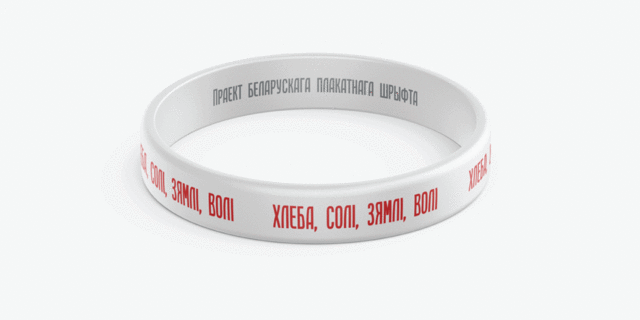
Гарнитура Хлеба Солі Зямлі Волі – это графическое исследование, объединяющее традиционный грубый жирный плакатный шрифт с гуманистическими нотками эпохи Возрождения. Гарнитура унаследовала некоторые идеи Франциска Скорины, чтобы добавить гуманистический оттенок. Название навеяно стихотворением Янки Купалы. Это современный белорусский титульный плакатный шрифт, но его можно легко использовать в любых случаях, когда необходимо сочетать строгие линии традиционных плакатов с гуманистическим стилем. Семейство шрифтов имеет 5 насыщенностей и 5 наклонных начертаний. Надписи этим шрифтом образуют сплошной блок. Шрифт разработал Алексей Коваль в 2020 году.
Всемирный День Джаза
Праздник Весны и Труда
9 мая День Победы